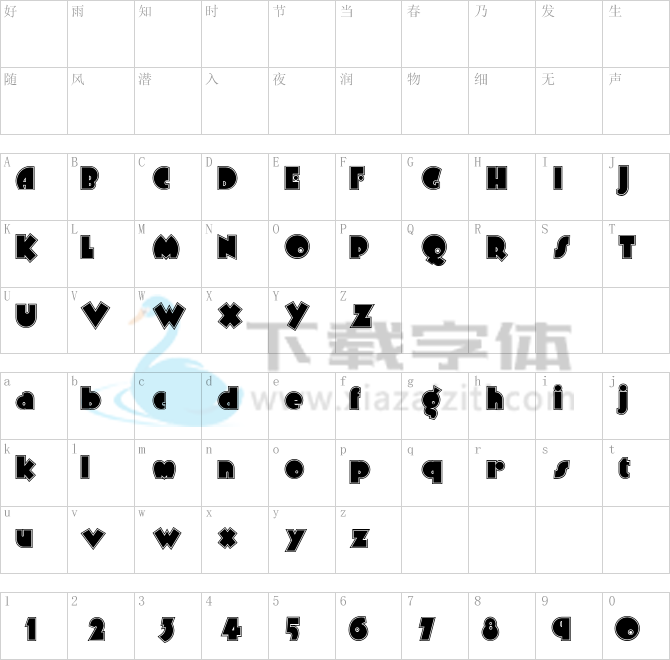
Arbuckle Inline NF.otf字体下载,这款字体结构工整、笔画清晰,兼顾美观与易读性,适用于标题、正文、海报、包装、LOGO 等多种场景。字形优雅稳定,风格百搭耐看,适配日常排版与创意设计,让文字呈现更舒适、更具质感。Arbuckle Inline NF.otf字体下载一笔一画,皆是细节,以均衡的比例、流畅的线条打造舒适视觉体验,字形端正大气,风格简约现代。无论是商业设计、品牌宣传还是日常排版,都能轻松驾驭,让文字更有格调与力量。Arbuckle Inline NF.otf字体下载字体下载。
• 字体名称:Arbuckle Inline NF
• 字体标识 ID:Nick'sFonts: Arbuckle Remix NF: 1997